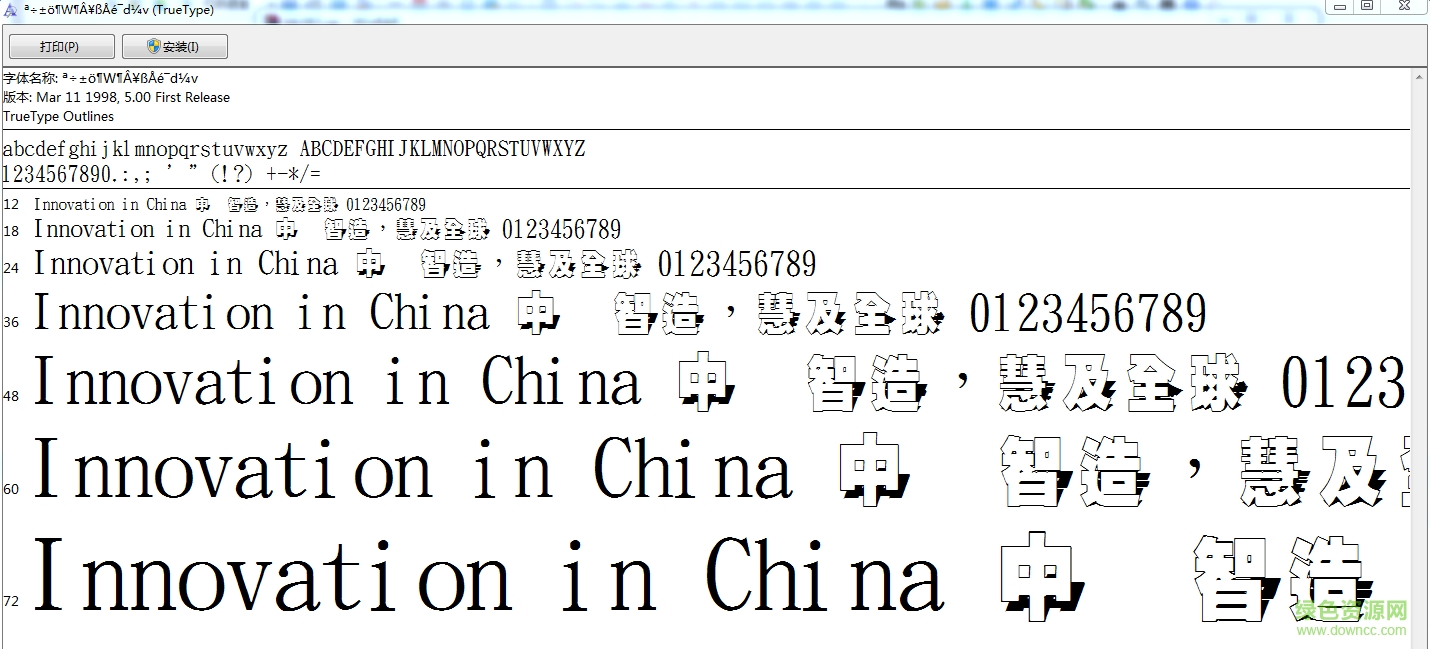
金梅超黑立體留影字體是一款比較立體的黑字這套,不得不說(shuō)使用這款字體打字的話效果還是很明顯的,設(shè)計(jì)平面廣告非常醒目!歡迎到綠色資源網(wǎng)下載體驗(yàn)!
金梅超黑立體留影字體效果整體上效果比較突出,金梅類立體字給人非常震撼的感覺,深受廣大書法家和年輕人的喜愛!